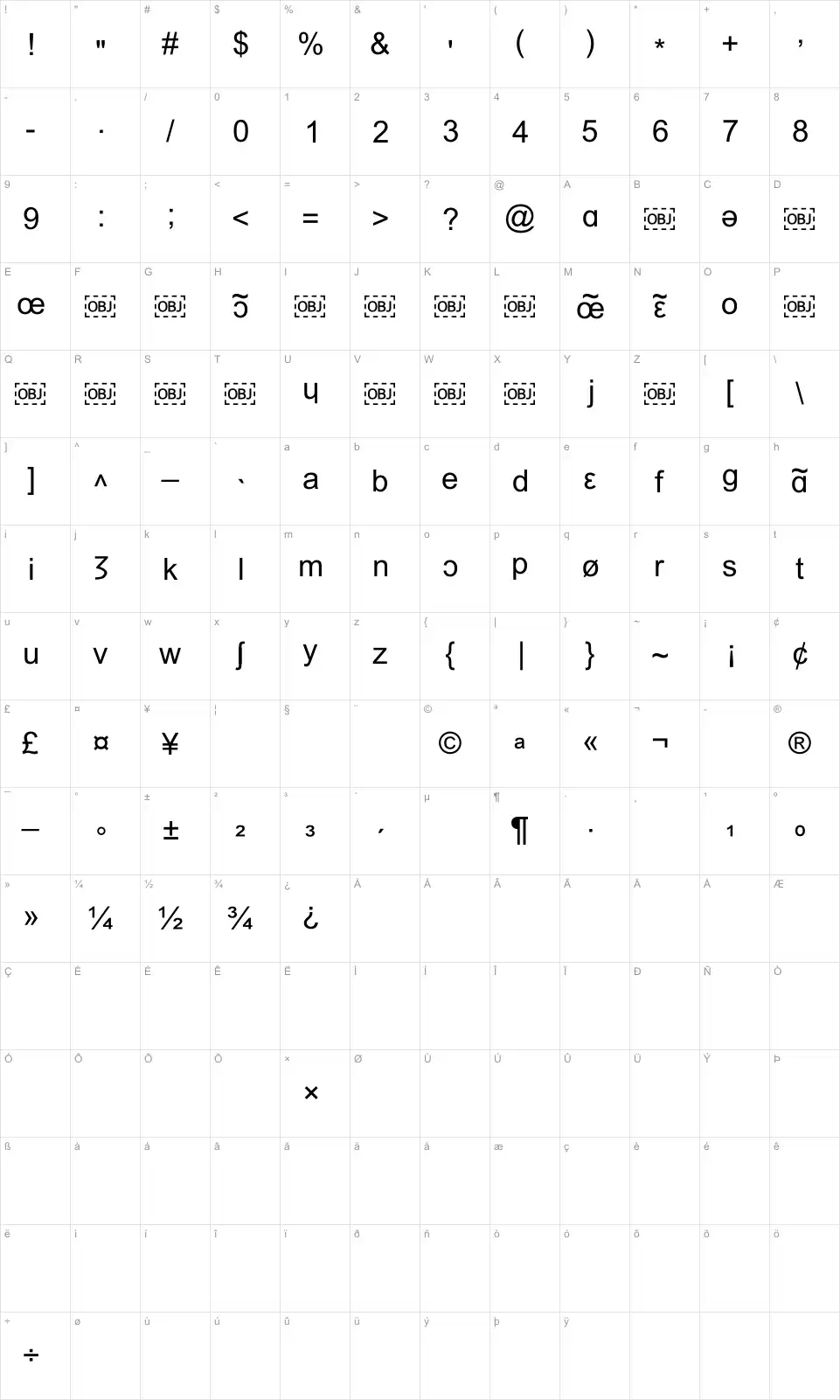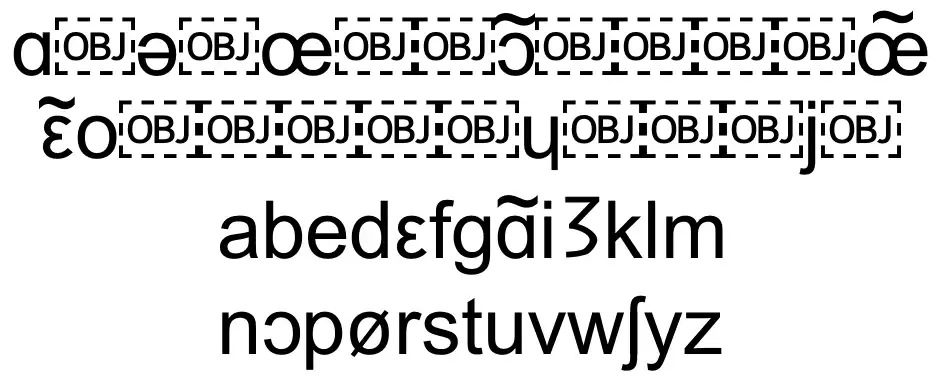
IPA Font
IPA Font é uma fonte criada pelo designer SlyveR, pertencente à categoria de Dingbats e adaptada para diversas utilizações. Esta fonte, licenciada sob a plataforma TTF, é uma excelente escolha para designers digitais e criadores de conteúdo que precisam de uma fonte única e diferenciada. Adicionada ao sistema em 12 de julho de 2022, IPA Font já se consolidou como uma opção popular para quem busca uma fonte específica para criar materiais de aprendizado, desenhos, arte digital ou qualquer outro tipo de material que exija um estilo visual único. Com um tamanho de 14 KB, é uma opção leve e eficiente para uso em dispositivos móveis. Para aqueles interessados em experimentar seu visual antes de usar, o site oferece a funcionalidade de gerar pré-visualizações de texto personalizadas, permitindo que você veja como a fonte ficará em qualquer texto digitado. Com mais de 5444 downloads desde sua publicação, IPA Font demonstra sua popularidade e qualidade.
Designer: SlyveR